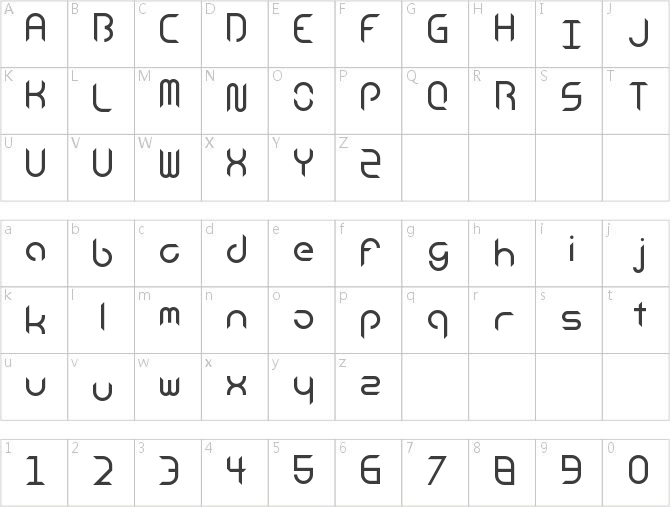
Android Insomnia Regular 詳情頁
字體名稱: Android
Android Insomnia Regular
Android Insomnia Regular介紹
Android Insomnia Regular字體字庫是一款讓人賞心悅目、百看不厭的英文字體,適合各類廣告和產品包裝設計應用,字體大小0.03MB,格式為ttf字體,上傳用戶是woslxn,作者/版權方為未知